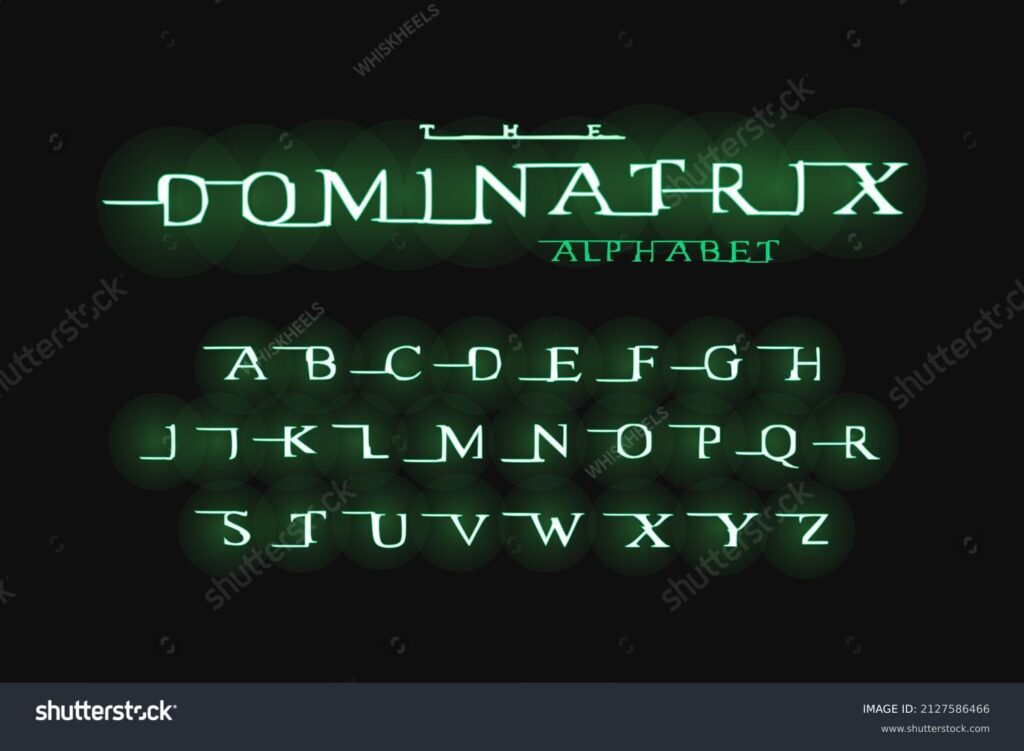
La Tipografía de The Matrix: Todo Sobre Ella
El torrente de caracteres verdes cayendo en cascada sobre un fondo negro es, sin duda, una de las imágenes más icónicas de la historia del cine. Desde su estreno en 1999, The Matrix no solo revolucionó la ciencia ficción y las escenas de acción, sino que también implantó en nuestra cultura una estética visual inconfundible. Muchos diseñadores, programadores y aficionados se han hecho la misma pregunta durante años: ¿qué fuente se usó para crear ese hipnótico código digital? La respuesta es más compleja y fascinante de lo que parece, ya que no estamos hablando de una sola tipografía, sino de varios conceptos que definieron la identidad visual de toda una saga.
En este artículo, nos sumergiremos en las profundidades de la Matrix para desentrañar el misterio detrás de sus fuentes. Exploraremos el origen del famoso "código de lluvia", diferenciaremos la tipografía utilizada en el logo y los pósteres, y te mostraremos cómo puedes emular esta estética en tus propios proyectos. Prepárate para tomar la píldora roja y descubrir la verdad sobre las letras que construyeron un universo.
El Mito del Código Verde: ¿Una Fuente Real?
La primera y más grande revelación es que el famoso código verde, también conocido como "Digital Rain" o "Matrix Code", no es una fuente tipográfica tradicional que se pueda instalar y usar en un procesador de textos. No fue creada por un tipógrafo, sino por un diseñador de producción: Simon Whiteley. Para la película, Whiteley necesitaba crear una representación visual de la propia Matrix, un flujo de datos constante que constituyera la realidad simulada en la que vivía la humanidad.
El origen de los caracteres es una de las anécdotas más curiosas del cine. Lejos de ser un complejo código informático, los símbolos son en realidad una mezcla de letras latinas, números y, sorprendentemente, caracteres del silabario japonés Katakana. ¿La fuente de inspiración? Los libros de cocina japonesa de la esposa de Whiteley. Él escaneó los caracteres, los manipuló digitalmente, los invirtió y los volteó para crear un aspecto que resultara familiar pero a la vez alienígena e indescifrable, representando perfectamente la naturaleza de la Matrix.
Por lo tanto, el código verde es más un efecto visual, una animación, que una fuente estática. Es la combinación de estos caracteres modificados, su color verde fosforescente sobre negro y su movimiento en cascada lo que crea la icónica imagen que todos conocemos.
La Verdadera Tipografía: El Logo y los Pósteres
Si bien el código de lluvia no es una fuente instalable, la saga sí utilizó una tipografía muy específica para su material promocional, incluyendo el título de la película y los carteles. Esta fuente, que muchos buscan creyendo que es la del código, se llama Matrix.
Diseñada por Audun Larsson Kleveland, esta tipografía originalmente se llamaba "Miltown". Su estilo desgastado, con caracteres que parecen fallar o "glitchear", encajaba a la perfección con la temática de una realidad digital defectuosa y corrupta. Las letras presentan cortes, distorsiones y una apariencia erosionada que evoca la desintegración del mundo simulado y la lucha de los rebeldes por liberarse. Fue la elección perfecta para encapsular la esencia de la película en una sola imagen: el título.
Así que, cuando alguien pregunta por la "fuente de The Matrix", es crucial diferenciar: ¿se refieren al efecto visual del código o a la tipografía del logo? La primera es un diseño a medida; la segunda es la fuente "Matrix" de Audun Larsson Kleveland.
Recreando la Lluvia Digital: Fuentes Inspiradas por Fans
La enorme popularidad del efecto del código verde llevó inevitablemente a que la comunidad de fans y diseñadores creara sus propias fuentes para emularlo. Estas tipografías no son las originales, pero hacen un trabajo fantástico al replicar la estética, permitiendo a cualquiera escribir con los famosos caracteres verdes.
Una de las más conocidas es Matrix Code NFI, diseñada por Norfok Incredible Font Design. Este tipo de fuentes, a menudo catalogadas como "dingbats" o decorativas, asignan los caracteres especiales de estilo Katakana y otros símbolos a las teclas de un teclado estándar. Al usarlas, puedes escribir párrafos que visualmente se asemejan al código que fluye en las pantallas de los ordenadores de la nave Nabucodonosor.
Estas fuentes son perfectas para proyectos de fans, fondos de pantalla personalizados, avatares, o incluso para darle un toque "hacker" a la terminal de tu ordenador. Sin embargo, es importante recordar que suelen tener licencias de uso específicas. Muchas son gratuitas para uso personal, pero pueden requerir un pago para fines comerciales.